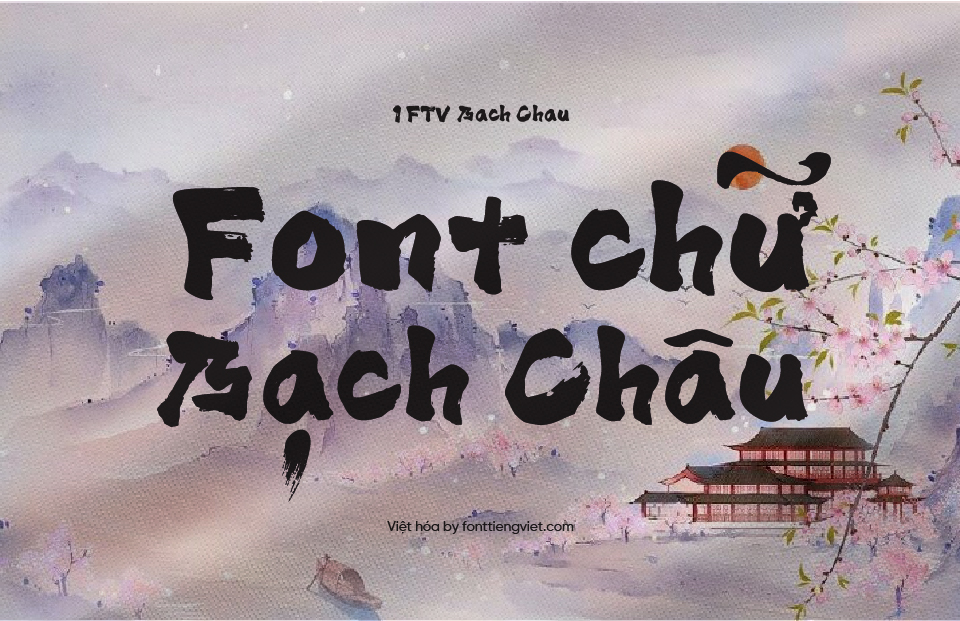
Font Việt hóa 1FTV Bach Chau – Thư pháp
Giới thiệu về Font Việt hóa 1FTV Bach Chau – Thư pháp
Trong thế giới đồ họa hiện đại, việc tìm kiếm một bộ Font Miễn Phí mang đậm bản sắc văn hóa dân tộc luôn là ưu tiên hàng đầu của các nhà thiết kế. Font Việt hóa 1FTV Bach Chau – Thư pháp là một tác phẩm nghệ thuật chữ viết độc đáo, kết hợp hoàn hảo giữa nét bút lông truyền thống và tư duy thẩm mỹ đương đại. Bộ font này không chỉ đơn thuần là những ký tự, mà còn chứa đựng cái hồn của thư pháp Việt, giúp mọi tác phẩm trở nên mềm mại và uyển chuyển hơn bao giờ hết.
Đặc điểm nổi bật của bộ font thư pháp này
Điểm ấn tượng nhất của Font Việt hóa 1FTV Bach Chau – Thư pháp chính là sự chỉn chu trong từng nét thanh, nét đậm. Các ký tự được tinh chỉnh kỹ lưỡng để phù hợp với hệ thống dấu tiếng Việt, tránh hiện tượng lỗi font phổ biến. Với phong cách phóng khoáng nhưng vẫn giữ được sự trang trọng, đây là lựa chọn lý tưởng cho các dự án thiết kế thiệp chúc mừng, bìa sách nghệ thuật hoặc các ấn phẩm văn hóa học đường.
Ứng dụng Font Việt hóa 1FTV Bach Chau – Thư pháp trong thiết kế
Nhờ tính linh hoạt cao, bạn có thể sử dụng bộ chữ này cho nhiều mục đích khác nhau. Trong môi trường giáo dục, giáo viên và học sinh có thể dùng font để trang trí bảng tin hoặc làm slide thuyết trình về lịch sử, văn học. Ngoài ra, các nhà thiết kế quảng cáo thường ưu tiên sử dụng font này cho các banner sự kiện Tết hoặc lễ hội truyền thống để tạo điểm nhấn thị giác mạnh mẽ.
Lưu ý khi sử dụng font thư pháp
Mặc dù sở hữu vẻ đẹp cuốn hút, người dùng nên kết hợp font với các kiểu chữ không chân đơn giản để đảm bảo tính dễ đọc. Việc lạm dụng quá nhiều chữ thư pháp trong một đoạn văn dài có thể gây rối mắt, vì vậy hãy sử dụng nó như một tiêu đề chính để tối ưu hiệu quả thẩm mỹ.